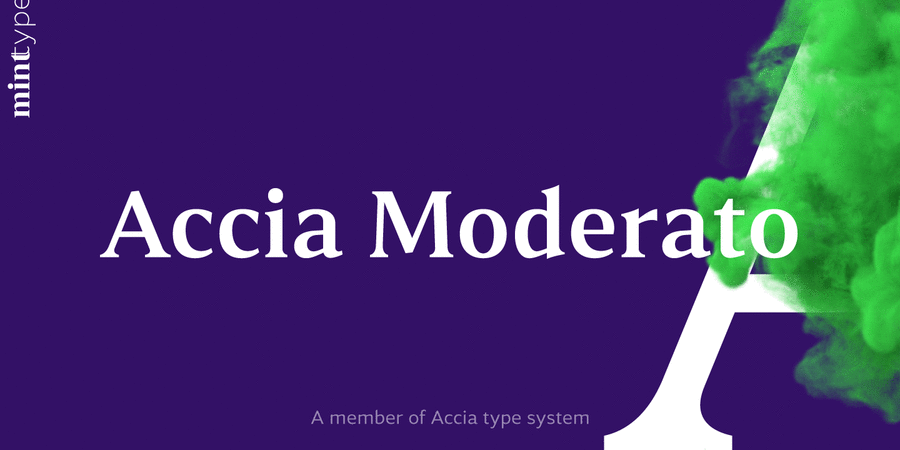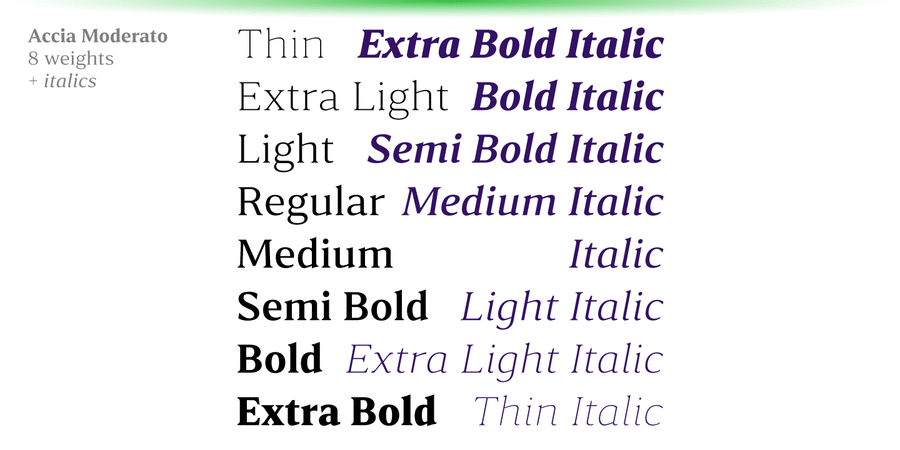
Опис гарнітури Accia Moderato – це сучасна антиква з помірним контрастом і великий висотою рядкових. Він стане відмінним вибором для основного тексту в книгах і журналах. Шрифтове сімейство містить 8 накреслень від Thin до Extra Bold з відповідними курсивами. Кожне накреслення має велику мовну підтримку, включно з кирилицею, а також численні функції OpenType: капітель, лігатури, кілька наборів цифр, пунктуація з урахуванням регістру, дроби й індекси. Accia Moderato є частиною супергарнітури Accia, куди входять п'ять шрифтів, від гротеску до виразної антикви. Це дає вам можливість проектувати максимально складні серії продукції або інформаційні системи. Система Accia складається з Accia Sans, Accia Flare, Accia Piano, Accia Moderato і Accia Forte. Гарнітуру розробив Андрій Константинов в студії Mint Type у 2021 році.
Асоціації з сімейством шрифтів Accia ModeratoОсобистість і характер гарнітури:
тонкий, худий, витончений, делікатний, легкий, модний, якісний, культурний, добірний, благородний, гармонійний, елітний, дорогий, красивий, майстерний, знаменитий, оригінальний, багатий, міський, прозорий, гострий, колючий, розкішний, художній, рівний, врівноважений, космополітичний, технічний, сучасний, точний, логічний, освічений, серйозний, розумний, твердий, чіткий, різкий, динамічний, ввічливий, комільфо, зрозумілий, діловий, помірний, практичний, доступний, формальний, тактичний, виразний, характерний, аристократичний, історичний, традиційний, ностальгічний, світський, цікавий, гуманітарний, стійкий, королівський, пафосний, імперський, яскравий, кам'яний, гордий, переконливий, авторитетний, дзвінкий, сильний, помітний, урочистий, амбітний, римський, владний, видовищний, грандіозний, великий, величний, монументальний, впевнений, архітектурний, значний, мотивуючий, відповідальний
срібло, АСМР, мода, музика, ресторан, розкіш, комільфо, Місто, люкс, годинник, бутік, література, освіта, культура, філософія, преміум, готель, шоколад, сервіровка, опера, театр, музей, історія, мистецтво, художник, золото, живопис, костюм, краватка, проза, юрист, адвокат, фінанси, правосуддя, економіка, геральдика, меморіал, пам'ятник, надгробок, скульптура, король, меч, антикваріат, карти, чай, архітектура, алкоголь, коньяк, банкнота, захід сонця, кава, віскі, Трофей, нагорода, гроші, детектив, бібліотека, суд, влада, вечір, імператор, архітектор, Біблія, взуття, ром Гарнітура асоціюється з віком: